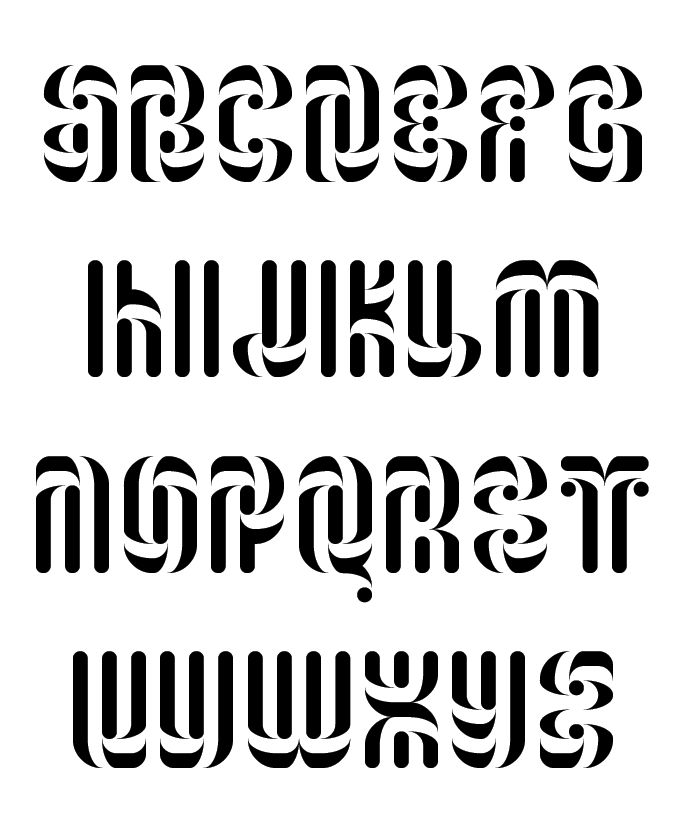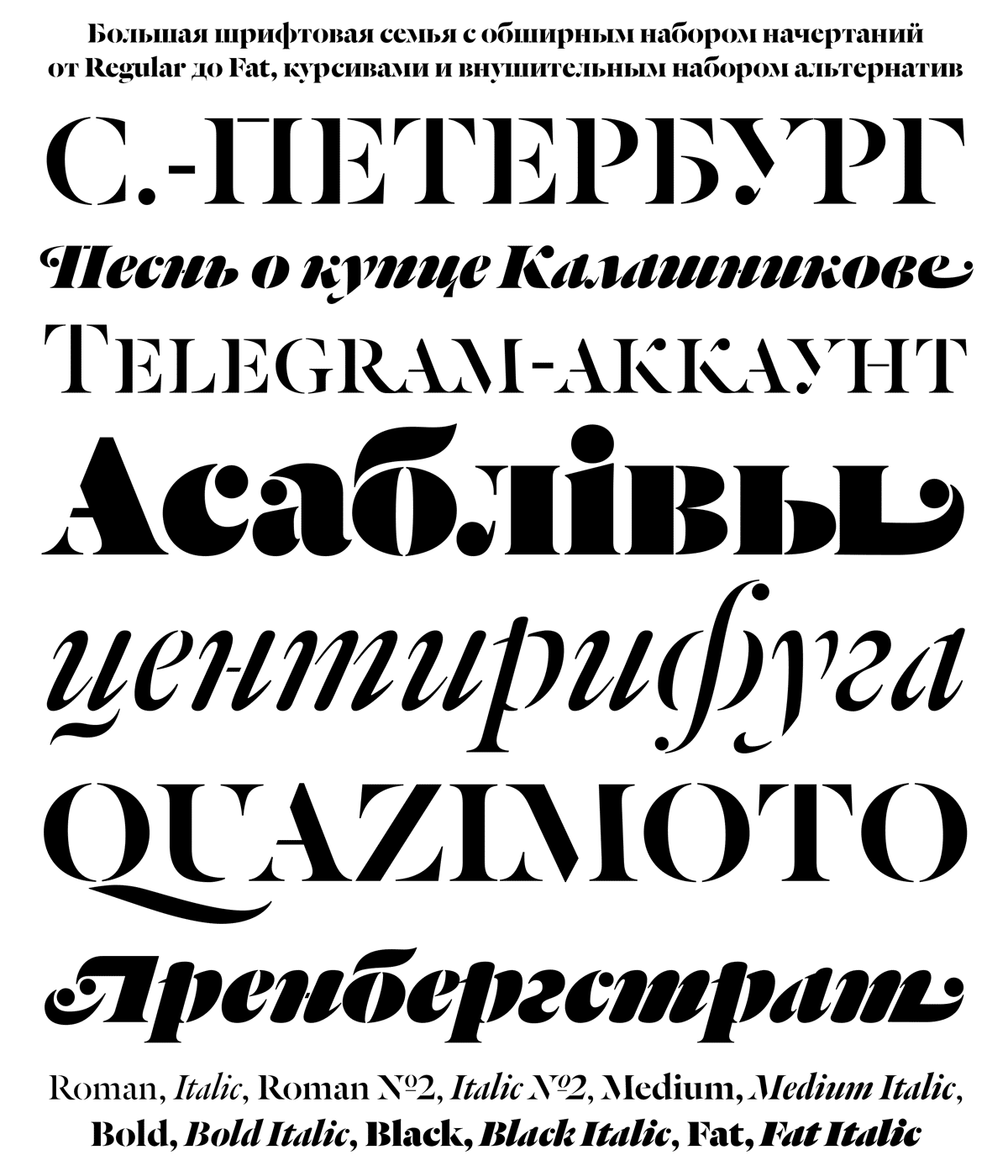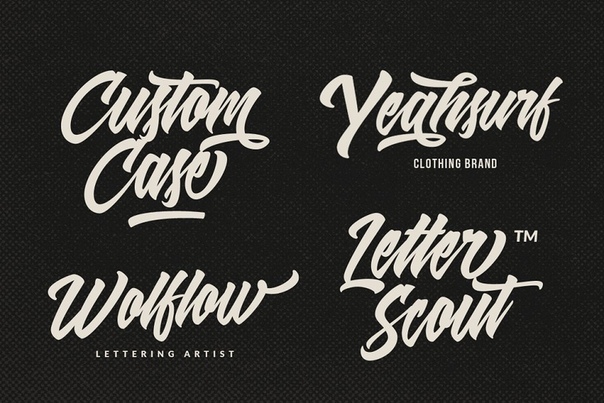
Шрифт кириллица дизайнерский: 42+ лучших кириллических шрифта бесплатно (обновлено в 2021)
20 бесплатных дизайнерских шрифтов — Искусство, дизайн, вдохновение — ReJump.ru
Радует, что дизайнерские шрифты появляются в сети чаще и создаются больше шрифтов русскими дизайнерами с поддержкой кириллицы. В нашей подборке вы сможете скачать 20 качественных шрифтов, которые сделают ваш проект лучше. Большинство собрано шрифтов на латинице, но есть парочка шрифтов на кириллице. Выбирай, скачивай и используй в своих дизайн проектах.
Бесплатный шрифт Quantify v2
Шрифт Cornerstone
Шрифт «Uphead»
Шрифт «Starforge»
Шрифт — California Hotel
Шрифт «Sansdria»
Шрифт «Familia»
Шрифт — Klark
Шрифт «Legendarie»
Шрифт «Modia»
Шрифт «Estoria»
Шрифт «Ratilla»
Шрифт «Florida»
Шрифт «Salazur»
Шрифт «Oakle»
Дизайнерский шрифт Quantum
Шрифт «FireFlight»
Шрифт «SwordFish»
Шрифт Edirne кириллица
Шрифт «EBENYA»
Дизайнерские кириллические шрифты. Лучшие бесплатные шрифты для дизайнеров
Типографика это искусство, в котором органично сочетаются техника, изобретательность и расчет на перспективу. За редким исключением хороший дизайн подразумевает хорошую типографику.
Многим дизайнерам, особенно новичкам, свойственно стремление ко всему новому. Они внимательно следят за всеми трендами в типографике и используют в дизайне самые новые и, как им кажется, «незаезженные шрифты». Это ошибка. Типографика дисциплина консервативная и новое здесь далеко не всегда означает лучшее.
- Дизайнер: Альберт-Жан Пул
- Дата выхода: 1995
- Издатель: FontFont
Шрифт FF DIN был создан голландским дизайнером Альбертом-Жаном Пулом. Первый вариант был представлен в 1995 году, затем разработка продолжилось и к моменту завершения работы в 209 году, семейство FF DIN включало в себя 20 начертаний. Шрифт отлично подходит для редакционного и издательского дела, а также может использоваться в рекламе и дизайне упаковки, в брендинге и других сферах творчества, таких, как дизайн плакатов и биллбордов. Хорошо выглядит FF DIN и на экране компьютера, так что его можно задействовать в веб-дизайне. У FF DIN имеется ограниченная поддержка кириллицы, что немаловажно для российских дизайнеров.
- Дизайнер: Ханнес фон Доррен
- Дата выхода: 2010
- Издатель: HVD Fonts
Brandon Grotesque – это очень известный шрифт без засечек, состоящий из шести наборов с различной толщиной штриха и шести соответствующих основным курсивов.
В основе шрифта лежат геометрические формы, оптически скорректированные для лучшей читаемости символов. Brandon Grotesque по праву считается функциональным и элегантным шрифтом. Начертания Light и Bold хорошо смотрятся на лайтбоксах или витринах, а Regular и начертания средней толщины подойдут для набора длинных текстов. Данный шрифт является отличным выбором для работы над проектами, где требуется типографика профессионального уровня. Brandon имеет расширенный набор символов для поддержки языков Центральной и Восточной Европы, но кириллицы нет, несмотря на то, что в списке языков русский присутствует.
- Дизайнеры: Сол Гесс, Моррис Фуллер Бентон
- Даты выхода: 1990-1995-2007
- Издатель: Monotype
Знаменитый шрифт Century Gothic во многом напоминает Futura, однако это уникальный шрифт, который является производным двух отдельных шрифтов ITC Avant Garde и Twentieth Century – основных конкурентов Futura. Century Gothic – это легкий, воздушный шрифт с чистыми и резкими окончаниями штрихов и очень хорошо проработанным курсивом.
Данный шрифт идеально подходит для заголовков или для набора крупными символами.
- Дизайнер: Марк Симонсон
- Дата выхода: 2005
- Издатель: Марк Симонсон
Семейство Proxima Nova представляет собой реконструкцию известнейшего шрифта Proxima Sans. Набор Proxima Nova был расширен до 48 полнофункциональных шрифтов Open Type. Новая Proxima состоит из трех больших групп, в каждой из которых по 16 шрифтов с различной толщиной штриха. Стилистически данный шрифт является сбалансированным сочетанием гуманистических пропорций и геометрического подхода к проектированию. Кириллица есть.
- Дизайнер: Адриан Фрутигер
- Дата выхода: 1998
- Издатель: Linotype
Шрифт Avenir также содержит отсылки к Futura, но в нем нет такой радикальной геометрии, как у его предка. У Avenir вертикальные штрихи толще, чем горизонтали и укороченные восходящие штрихи. Это идеальный выбор если требуется набрать хорошо читаемый текст.
- Дизайнеры: Эдуард Хоффман, Макс Мидингер
- Дата выхода: 1983
- Издатель: Linotype
Helvetica является одним из самых популярных шрифтов в истории мировой типографики, этот шрифт оказал огромное влияние как на рекламу, так и на маркетинг.
Автор
Уильям Монтроуз,
Слава Евчинова,
Давид Бржезина
Год создания
2019
Балдуфа
Автор
Ферран Милан,
Пилар Кано
(Letterjuice)
Год создания
2019
Зангези Санс
Автор
Дарья Петрова
Год создания
2019
Корса Гротеск
Автор
Александр Неделев
Год создания
2019
Maver
Автор
Ани Димитрова
Год создания
2019
Grafema LC
Автор
Жаклина Жекова,